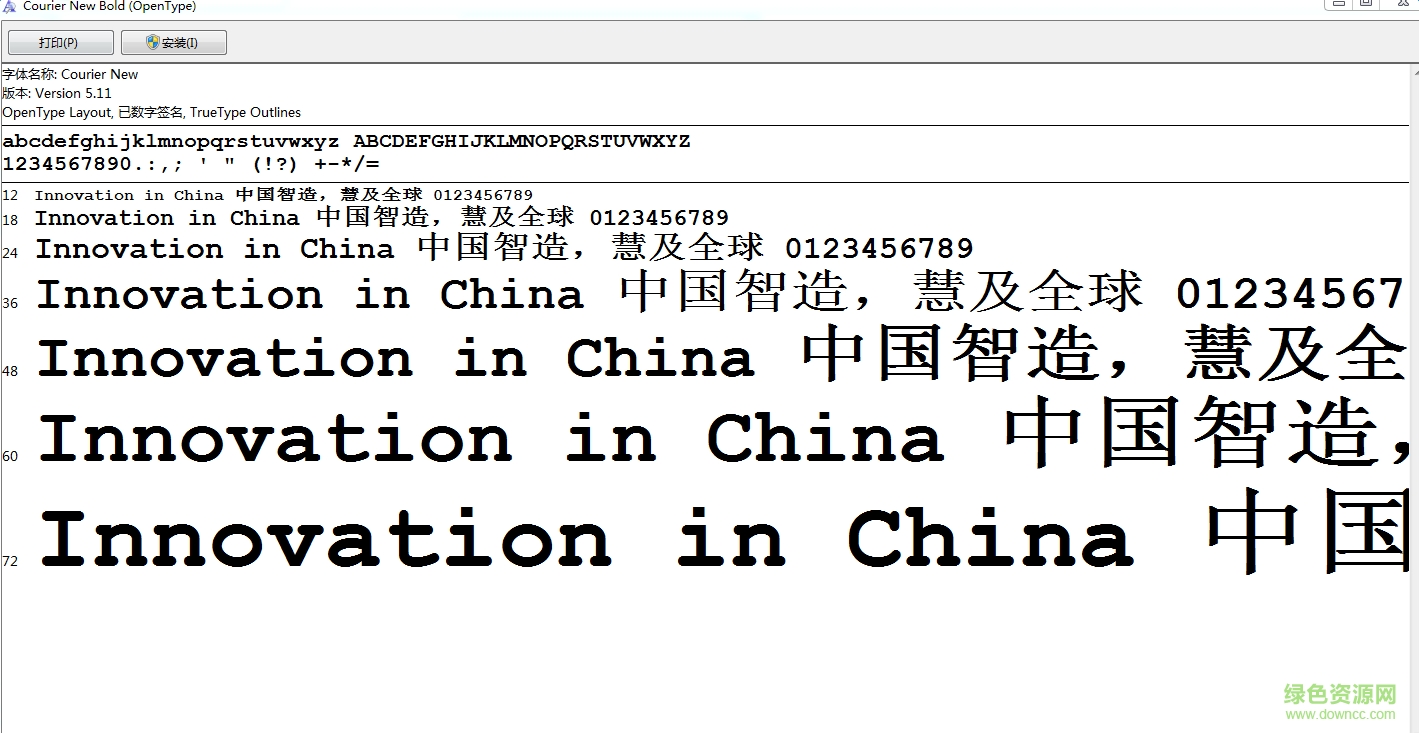
couriernewpsmt字體是一款常見的英文字體,該字體符寬度相同,筆形簡練,清晰度高,排版效果比較自然,適于網(wǎng)頁設(shè)計(jì)、編程用字等,歡迎大家在綠色資源網(wǎng)免費(fèi)下載!
1.早期的電腦顯示器、打字機(jī),由于技術(shù)的局限,無法進(jìn)行字母寬度的比例調(diào)整,因此將每個(gè)字元都制作成一樣的寬度,從而形成了等寬字體。
2.但是隨著圖形用戶界面主流的更新和電腦技術(shù)的提高,處理比例字體的局限性得到了突破,因此現(xiàn)在排版上顯得比較自然的比例字體的使用已經(jīng)相當(dāng)普及。
3.但是一些中文、日文字體中,由于同時(shí)涵蓋西文的半形文字字符,因此也含有比例字體,造成一個(gè)字體中兩種類型混雜的局面。